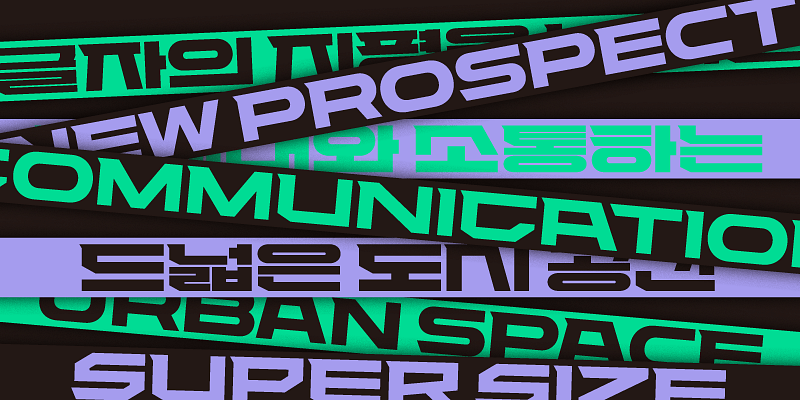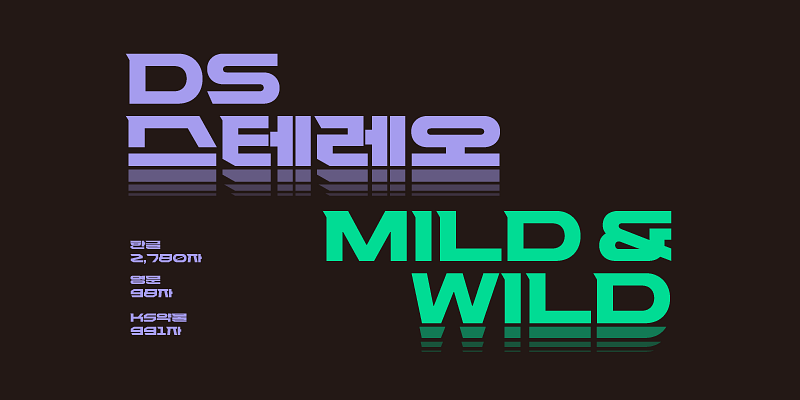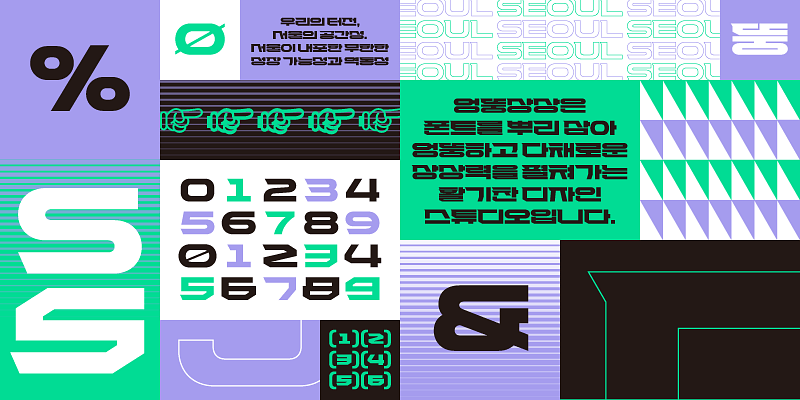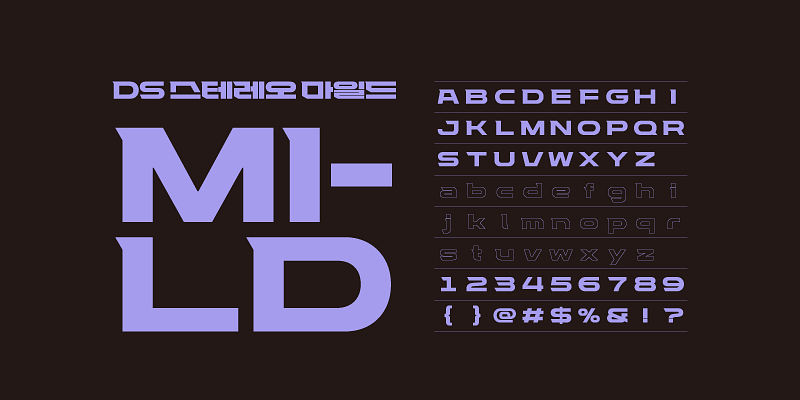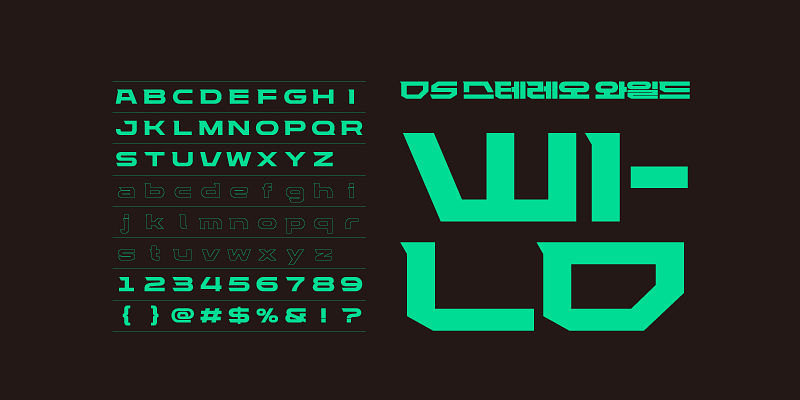
Ispirato agli ampi spazi urbani, DS Stereo è un font di grandi dimensioni che brilla davvero se utilizzato in grafica di grandi dimensioni. La sua presenza dominante da sola può trasformare il tuo lavoro in un pezzo audace e alla moda. Con i suoi angoli dinamici e un tocco di fascino retrò, DS Stereo è abbastanza versatile da comunicare attraverso tutte le generazioni.